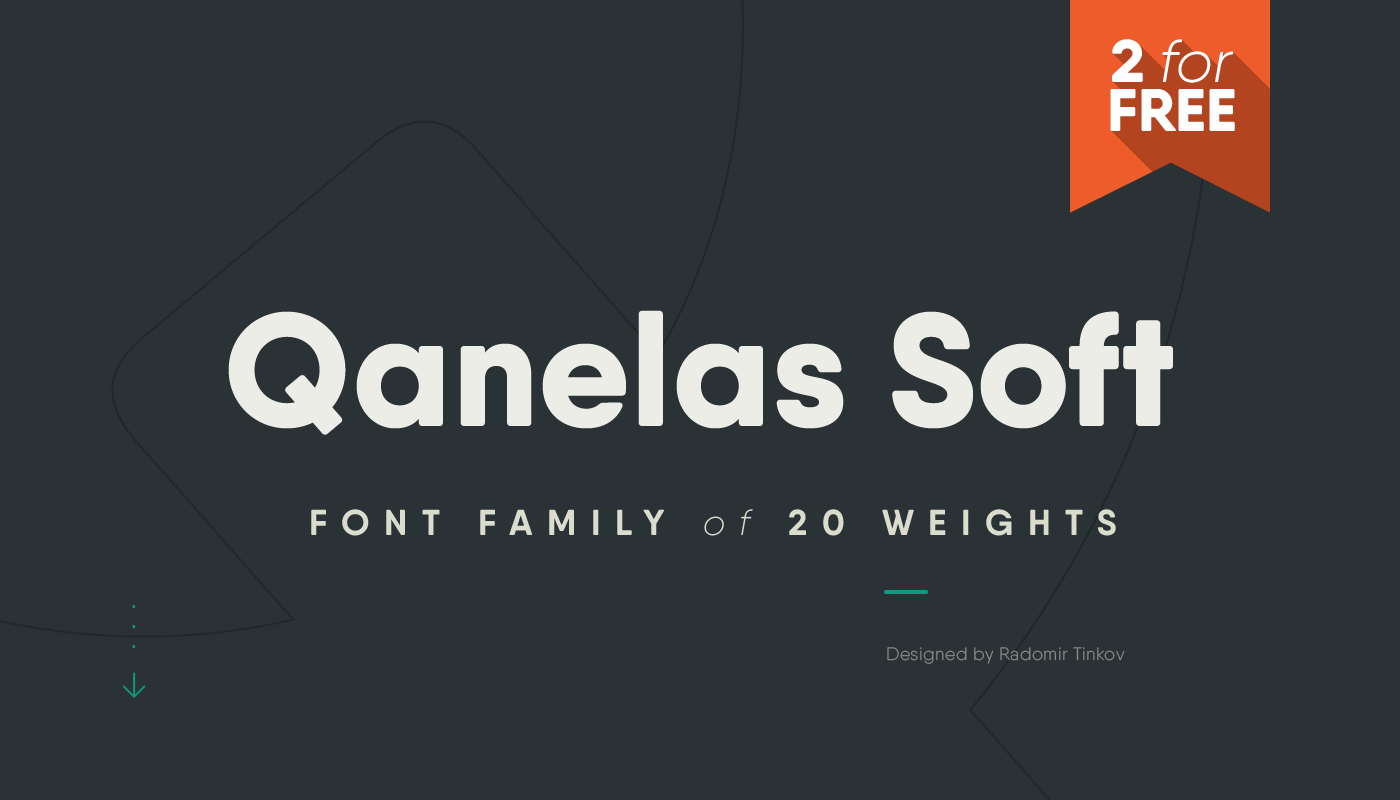
Qanelas Soft: 3 Free font weights – Download Grátis
QanelasSoft é uma fonte sans-serif moderna com uma pontada geométrica que oferece um toque fresco para quem está procurando algo mais leve e amigável na sua tipografia. Desenvolvida pelo designer Hamilton, essa família de fontes inclui 3 pesos livres – normal, médio e extremamente fino -, além de suas respectivas itálicas. As opções de peso oferecem alternativas de caracteres, frações, suporte linguístico para mais de uma língua (incluindo o cirílico), símbolos arábicos e ligaturas, fornecendo um leque rico em recursos OTF que se assemelha a um conjunto completo de fontes. Escolhida por designers gráficos, é perfeitamente adequada para uso em qualquer formato de mídia visual. Desde aplicativos de redes sociais até design editorial e identidade corporativa, QanelasSoft é uma fonte versátil que se destaca como um recurso vital no arsenal do designer moderno. Suas características únicas e potentes ottf features permitem uma personalização impecável que complementa qualquer projeto visual, tornando-se uma opção ótima para qualquer aplicação de design digitais ou offline.